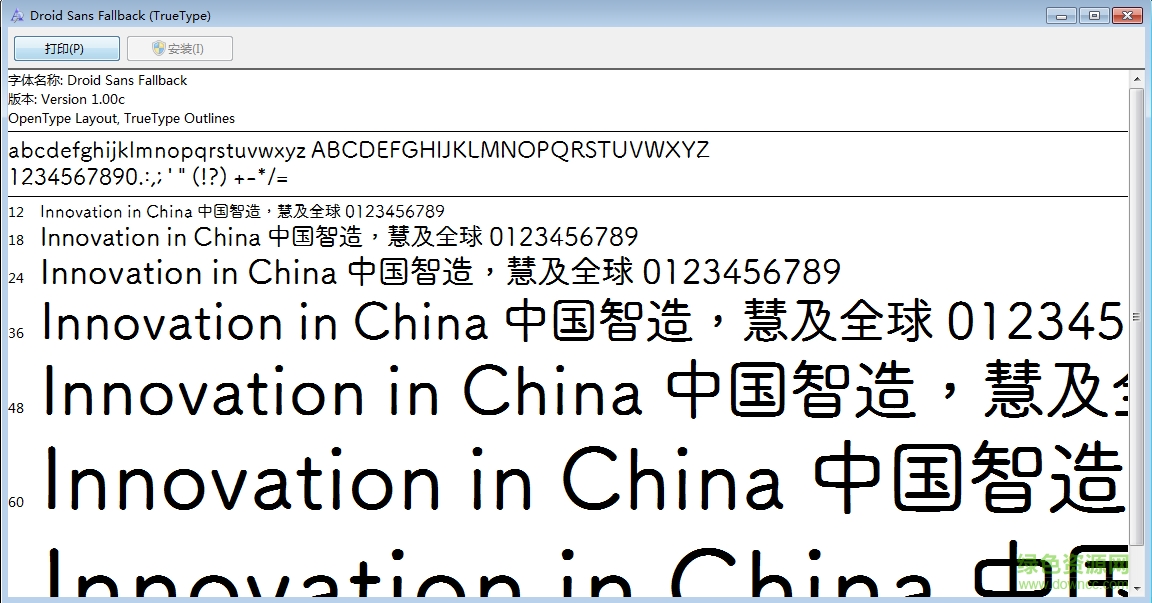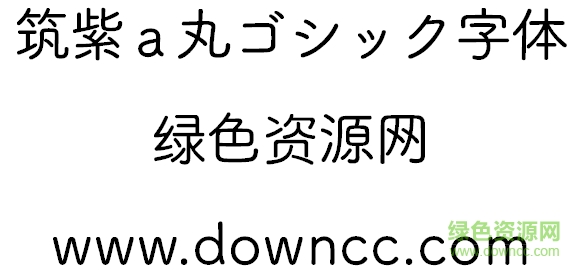
筑紫a丸ゴシック是一款提問字體,支持中文繁簡(jiǎn)輸入,字形簡(jiǎn)約流暢給你舒適視覺體驗(yàn),大方秀氣的造型也深受創(chuàng)意設(shè)計(jì)、廣告制作、排版印刷等人士喜愛,歡迎大家來(lái)綠色資源網(wǎng)免費(fèi)下載!
符合簡(jiǎn)約口味,支持簡(jiǎn)體、繁體、日文、韓文,生僻字也都檢查過正常,沒有剃頭剃尾現(xiàn)象,自帶彩色emoji表情。
筑紫a丸是一款深受手機(jī)黨們喜愛的日文字體,支持中文繁簡(jiǎn)語(yǔ)言,國(guó)人使用起來(lái)也方便無(wú)壓力,是一款很漂亮的藝術(shù)字體!